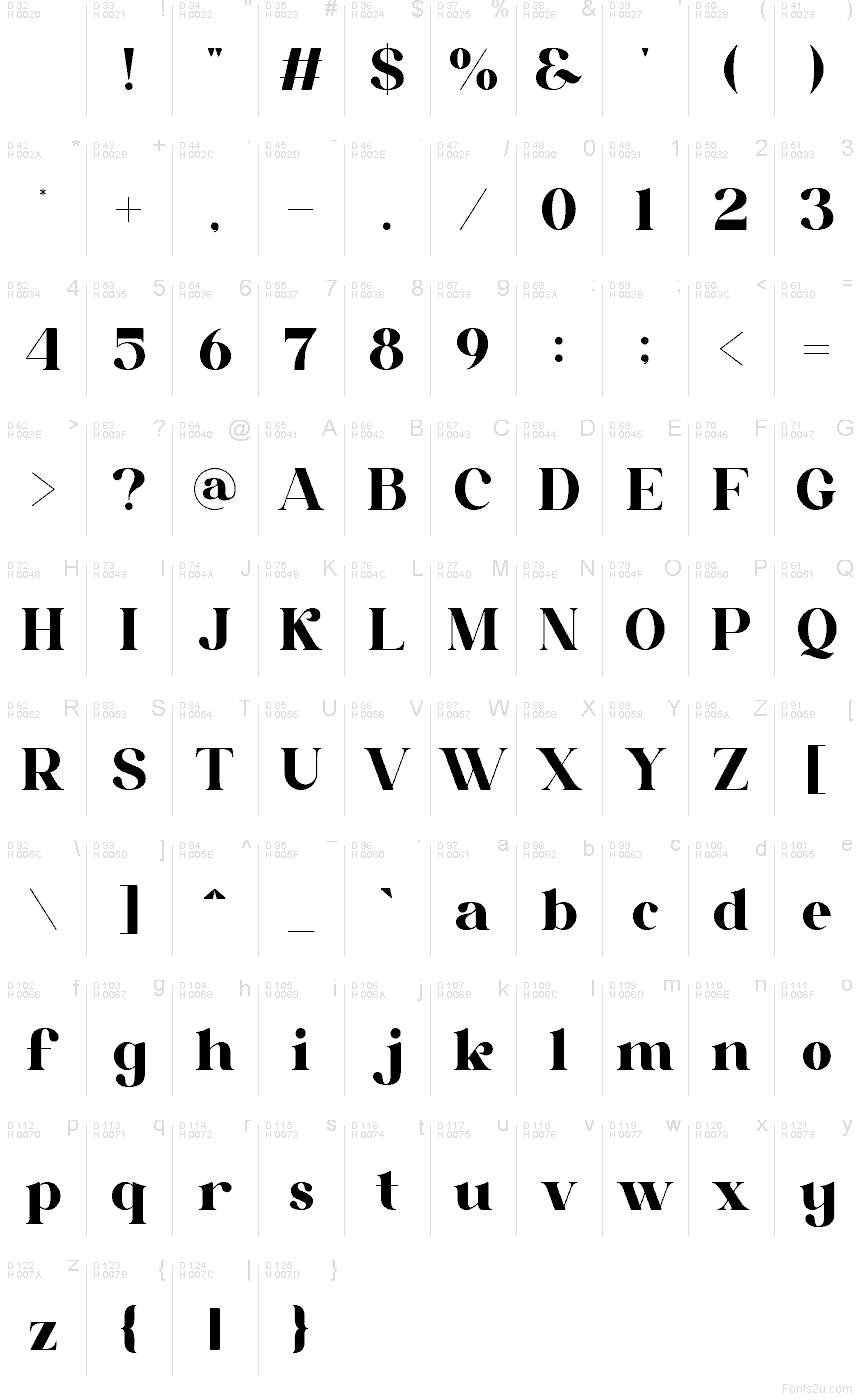
Rinova, criada pelo Ermedia Studio, é uma fonte serifada gratuita de alto contraste, com um caráter Didone refinado e um estilo editorial distinto. Curvas amplas e esculturais encontram traços finos como fios de cabelo, enquanto serifas nítidas e o ponto arredondado criam um ritmo equilibrado e sofisticado.
Use esta fonte gratuita em cabeçalhos de revistas, branding de luxo, embalagens de fragrâncias, capas de livros e cartazes culturais. O seu contraste dramático também é perfeito para títulos curtos, onde as curvas generosas e os detalhes precisos têm espaço para impressionar.